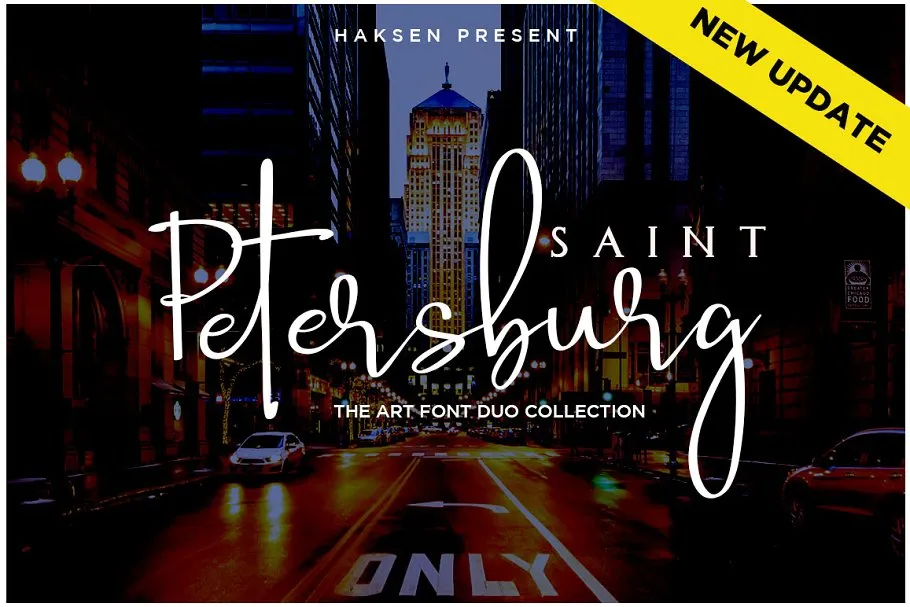
Saint Petersburg Font Duo – Fonte Grátis
Saint Petersburg Font Duo
A Saint Petersburg Font Duo é uma combinação única de letras que traz ao design a sofisticação dos textos manuscritos, perfeita para quem busca uma estética elegante e versátil. Criada pelo talentoso designer 0001themes, esta fonte do script oferece um toque refinado capaz de dar vida aos seus projetos. Com sua aparência fluida e natural, Saint Petersburg Font Duo é ideal tanto para aplicações comerciais quanto pessoais, sem comprometer a qualidade ou a estética. A fonte não só atende à necessidade de uma tipografia criativa para seu projeto específico, como também permite que você personalize o texto com uma elegância discreta e sofisticada. É um verdadeiro prazer compartilhar Saint Petersburg Font Duo em sua biblioteca, sabendo que cada caractere é capaz de tornar qualquer layout mais profissional e sofisticado. Seja para criar gráficos, designs digitais ou qualquer outro tipo de aplicação de texto personalizada, esta fonte se revela uma peça indispensável no seu arsenal criativo.